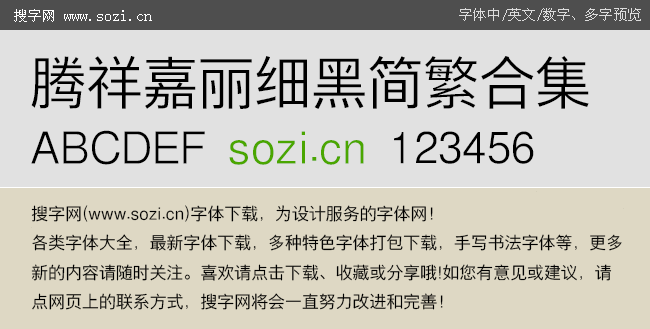
騰祥嘉麗細(xì)黑簡繁合集
搜字網(wǎng)提供一款騰祥嘉麗細(xì)黑簡繁合集中文藝術(shù)字體下載,騰祥嘉麗細(xì)黑是一款端正的黑體字體,該字體大方得體,整體效果出眾,并且字庫完整,可用于藝術(shù)設(shè)計(jì)、包裝印刷、簽名設(shè)計(jì)、圖形設(shè)計(jì)等領(lǐng)域。